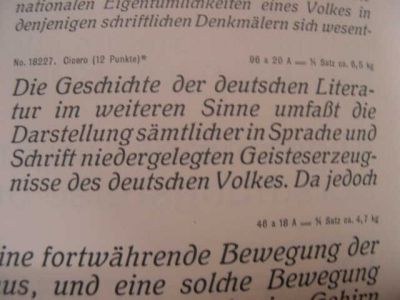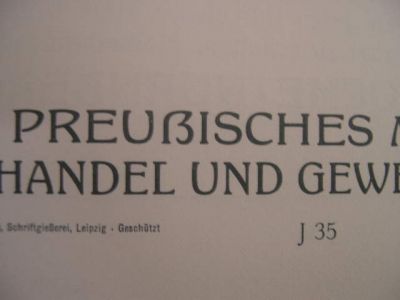
Schriftmusterb. d. Schriftgießerei Schelter & Giesecke
weiß jemand, wo die Schriftmusterbücher von 1906 bis 1931 der Schriftgießerei Schelter & Giesecke, Leipzig archiviert sind?
Ist da die Schelter kursiv von 1906 noch dabei?
Schelter-Kursiv No. 24
Komplette Zeichensätze werden fast nie abgebildet.
Hast Du auch eine Seite, wo das große ß dieser Schrift abgebildet ist?
Das ß ist aus der Breiten Schelter-Antiqua No. 25
Der Text darüber aus der normalen Schelter-Antiqua No. 24
Wie ist hiebei die No. 24 zu verstehen?
das weiß ich nicht.
Die normale Schelter-Antiqua hat im Buch die No. 24, die breite die No. 25.
Aber vermutlich nur eine Zuordnung verschiedener Versionen.
Ähnlich, wie bei der Aurora:
Garnitur IV fett
Garnitur I mager
Garnitur VII breithalbfett
Garnitur VI breitmager
Bei den digitalen Fonts gibt es doch auch manchmal zusätzliche Bezeichnungen in Form von Nummern.